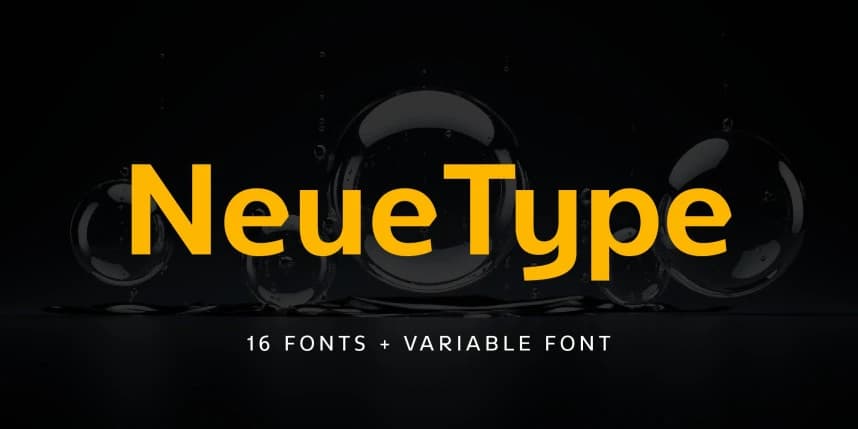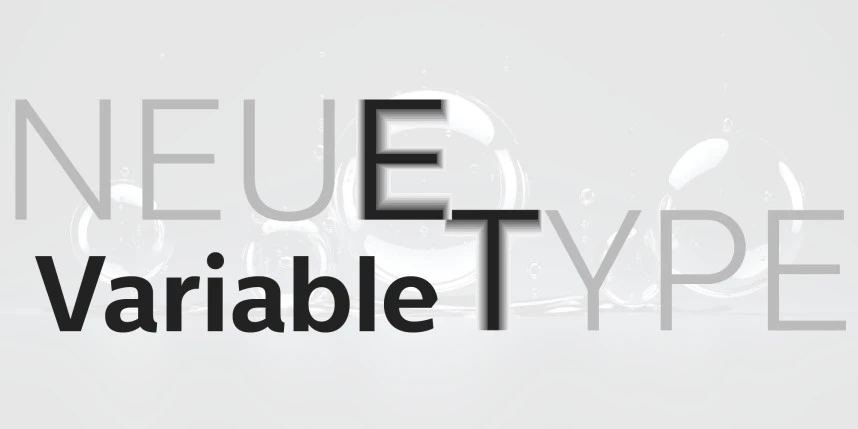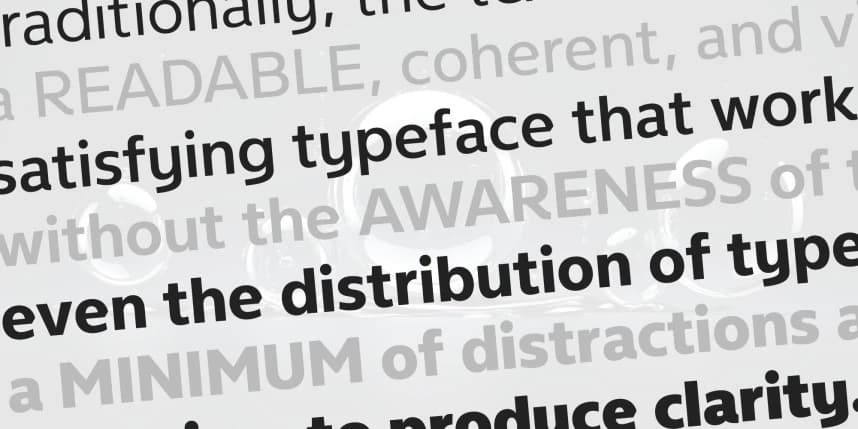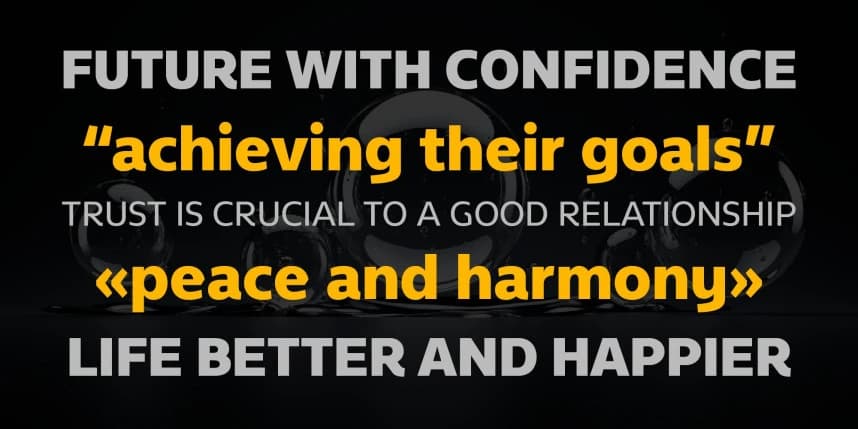
NeueType Font
NeueType Font, modern bir sans serif yazı tipi ailesidir. Bu aile web ve baskı için idealdir. 16 farklı kalınlıkta, 8 düz sürüm ve eşleşen italiklerle birlikte, ayrıca Değişken yazı tipi olarak sunulur. Her bir kalınlık 570 glif içerir ve 22 OpenType özelliğine sahiptir (Ligatürler, Büyük/Küçük Harf
NeueType Font modern bir sans serif yazı tipi ailesidir. Bu aile web ve baskı için idealdir. 16 ağırlık, 8 düz yazı ağırlığı ile eşleşen italikler ve Değişken font ile birlikte sunulur. Her bir ağırlık 570 glif içerir ve 22 OpenType özelliğine sahiptir (Ligatürler, Harf Duyarlı Biçimler, Sıra Sayıları, Tablo Rakamları, Büyük Harf Aralığı, Çizgili Sıfır ve Tipografik Varyantlar dahil).